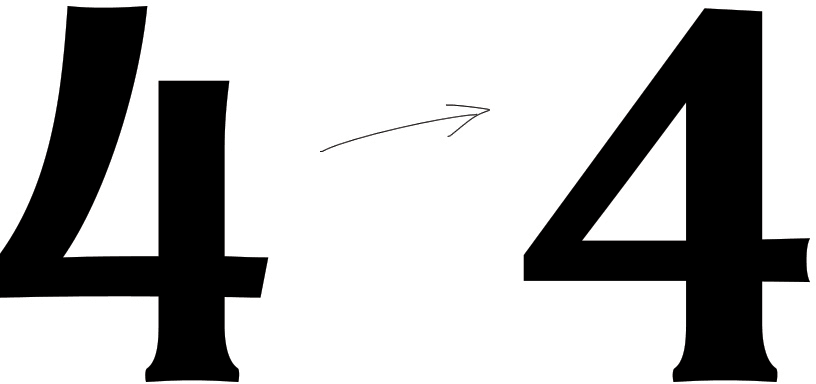
Старомосковский шрифт: особенности фирменного шрифта Москвы
В 2014 году в дизайн-студию Артемия Лебедева поступил заказ на создание фирменного шрифта для Москвы. Заказчиками выступили комитет по архитектуре и градостроительству вместе с главным архитектурно-планировочным управлением Москомархитектуры.
Цель — систематизация и улучшение адресной организации в городе. Дизайнером проекта была назначена Ксения Ерулевич, а в роли арт-директора остался сам Артемий Лебедев. Помимо нового шрифта в рекомендации вошли также цвета, пиктограммы и принципы верстки для домовых табличек.
Чтобы сохранить старый дух города, шрифт было решено сделать на основе старых домовых табличек. Дизайнеры нашли несколько образцов, которые в дальнейшем стали основой. Подобрав референсы – вспомогательные изображения, – команда стала создавать новый Старомосковский шрифт. Для передачи духа было выбрано несколько основополагающих особенностей: пропорции, контраст, треугольные засечки, узость буков и ширина цифр. В итоге формы нового шрифта были похожи на старый, но оказались не столь архаичными.
Этот дизайн был создан исключительно для навигации по Москве, имеет два начертания: прямое и широкое жирное. Первое для названий объекта, второе же для цифр и родовых понятий (бульвар, проспект).
Верстка и дизайн адресных знаков зависит от места, где висит табличка.
- Для пешеходных зон, которые наполнены памятниками архитектуры и предназначены для отдыха и эстетического наслаждения, указатели оформлены соответственно, на основе указа московских властей.